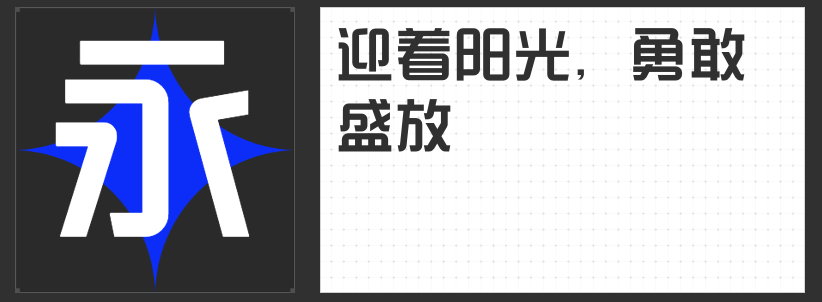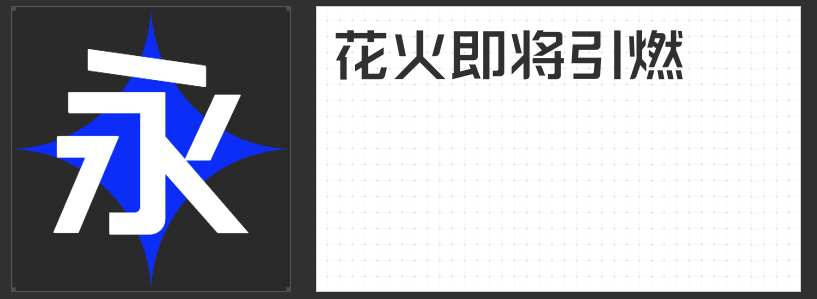
现代设计新宠:四款独具魅力的字库字体推荐
在追求创新与美感的现代设计领域,字体的选择往往成为决定作品风格的关键因素。以下四款字体凭借其独特的设计理念与视觉表现力,成为设计师们打造现代感作品的理想之选。
一、励字超级勇士简 常规
这款黑体以现代几何化设计为核心,通过精准的笔画比例与结构布局,构建出严谨而稳定的视觉框架。其笔画线条虽简洁,却通过微妙的弧度处理赋予字体柔和气质,既保留了黑体的力量感,又避免了生硬感。中宫紧凑的设计使文字在排版中更显精致,适合需要兼顾专业性与艺术性的场景,如品牌视觉系统、高端产品包装等。
二、励字勇敢黑简 中黑
作为无衬线字体的代表,这款字体以粗壮笔划塑造出强烈的视觉冲击力。其笔画末端采用平切处理,撇捺等笔画去尖化设计,既保证了文字的清晰可读性,又通过均匀的横竖比例营造出平衡感。中黑字重的设计使其在标题、导语或标志等需要突出显示的场景中表现尤为出色,能够瞬间抓住观者注意力,传递品牌的核心信息。
三、励字圆梦简 中黑
这款字体通过直线与圆弧的巧妙融合,创造出独特的视觉语言。以竖折笔画替代传统弧线的设计,既简化了字形结构,又保留了文字的灵动性。笔画起收处的自然圆弧处理,搭配外圆内方的中宫布局,使字体在柔和中蕴含力量感。其适中的字重与松散的中宫设计,特别适合需要营造温馨、亲和氛围的场景,如文化创意产品、儿童教育类设计等。
四、创客贴综艺体常规
基于黑体框架的创新设计,这款字体通过将笔画转折处转化为圆弧处理,彻底打破了传统字体的生硬感。圆滑的线条过渡与均匀的笔画粗细,赋予字体时尚而活泼的气质。作为一款创意字体,其设计既保留了黑体的易读性,又通过独特的造型语言传递出年轻化、个性化的品牌态度,非常适合用于综艺节目、社交媒体、潮流品牌等需要突出视觉张力的场景。
这四款字体通过不同的设计路径,共同诠释了现代字体设计的核心价值——在功能性与艺术性之间寻找平衡点。无论是追求严谨优雅、力量感、柔和诗意还是创意突破,它们都能为设计师提供丰富的表达可能,助力打造出更具现代感与辨识度的视觉作品。